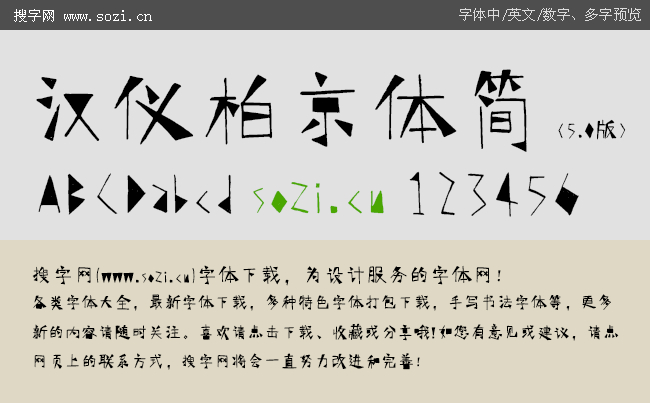
漢儀柏京體簡(jiǎn)5.0版
搜字網(wǎng)提供漢儀柏京體簡(jiǎn)中文藝術(shù)字體下載,漢儀柏京體技術(shù)上借鑒了歐式傳統(tǒng)鋼筆的剛勁筆鋒, 三角形和線條的組合產(chǎn)生了表現(xiàn)主義的豪放效果。字體風(fēng)格活力蓬勃,筆勢(shì)伸展如龍蛇舞動(dòng),同時(shí)又受歐陽體的影響,結(jié)構(gòu)布局是平正工整,嚴(yán)謹(jǐn)峭勁,有疏有密,穩(wěn)中而生動(dòng)。。可以應(yīng)用于廣告設(shè)計(jì)、名片設(shè)計(jì)、包裝印刷、產(chǎn)品設(shè)計(jì)等應(yīng)用。